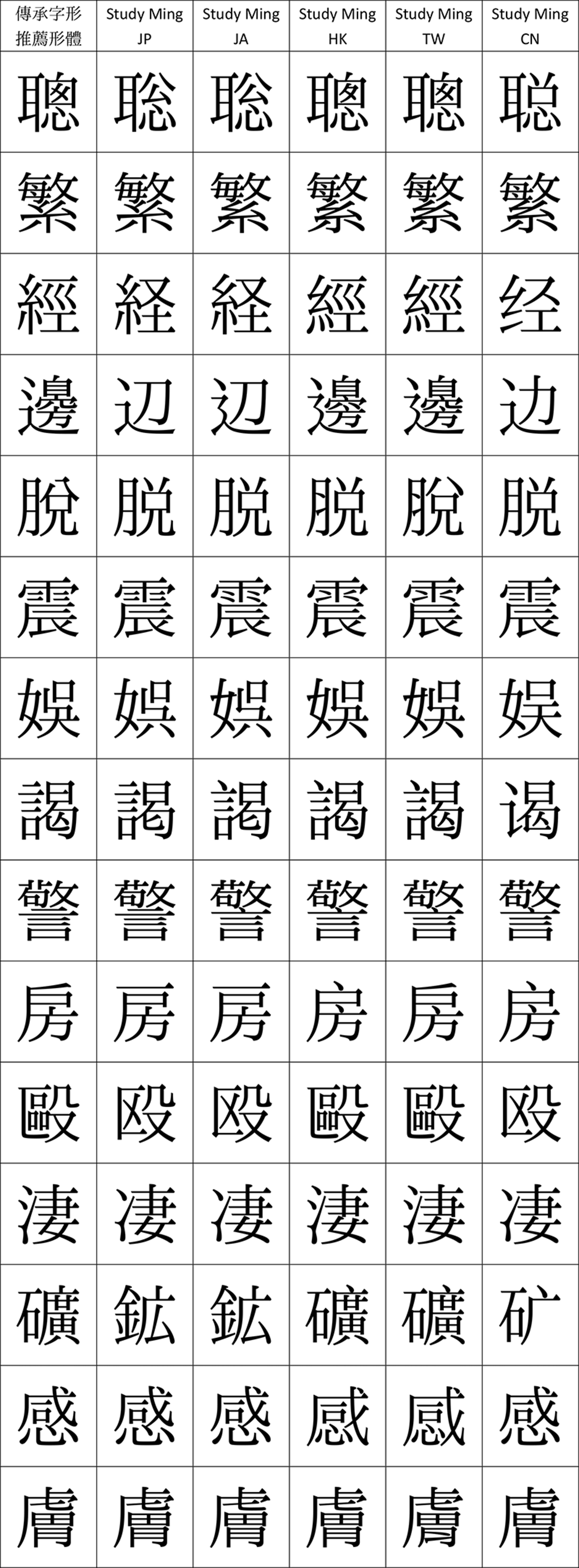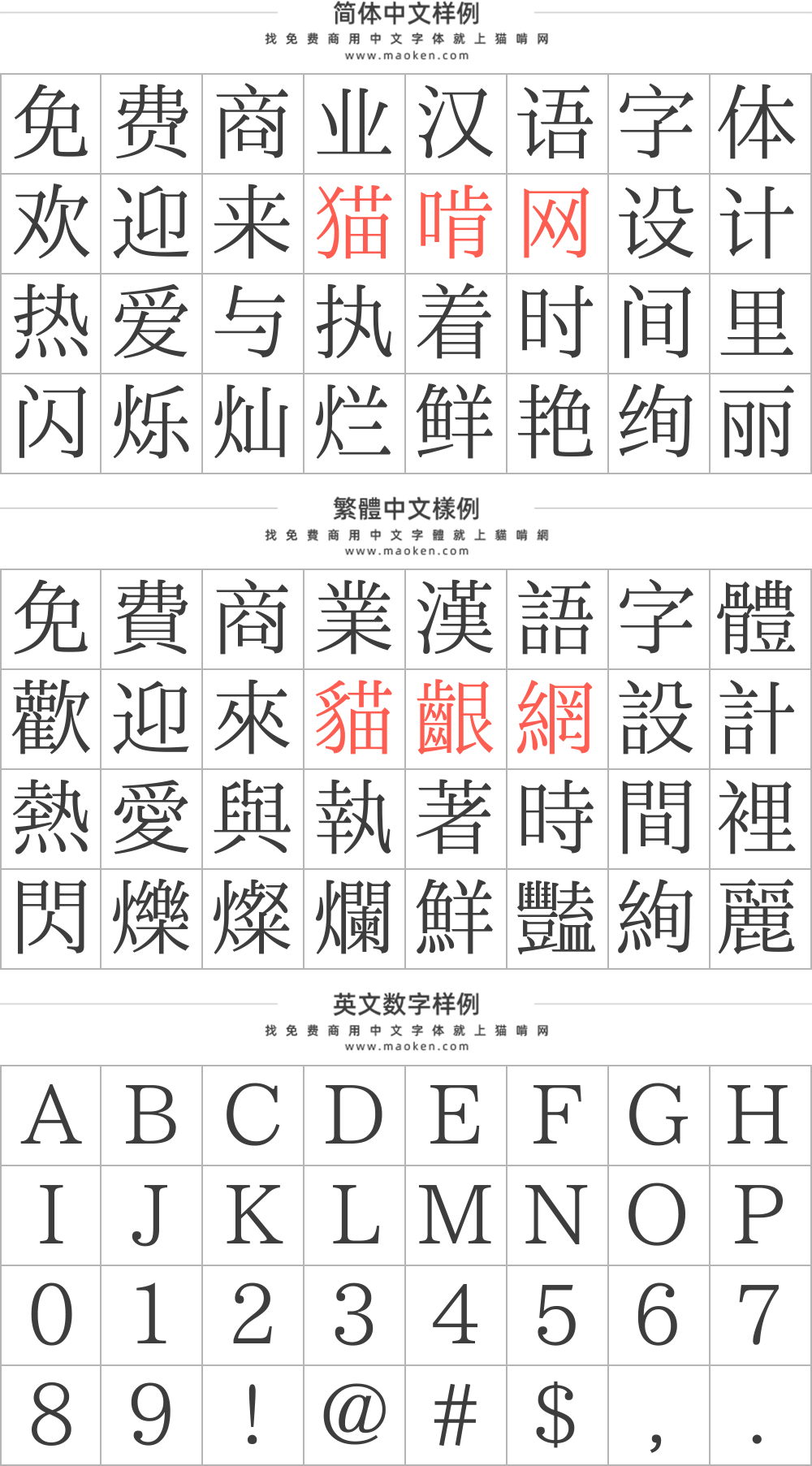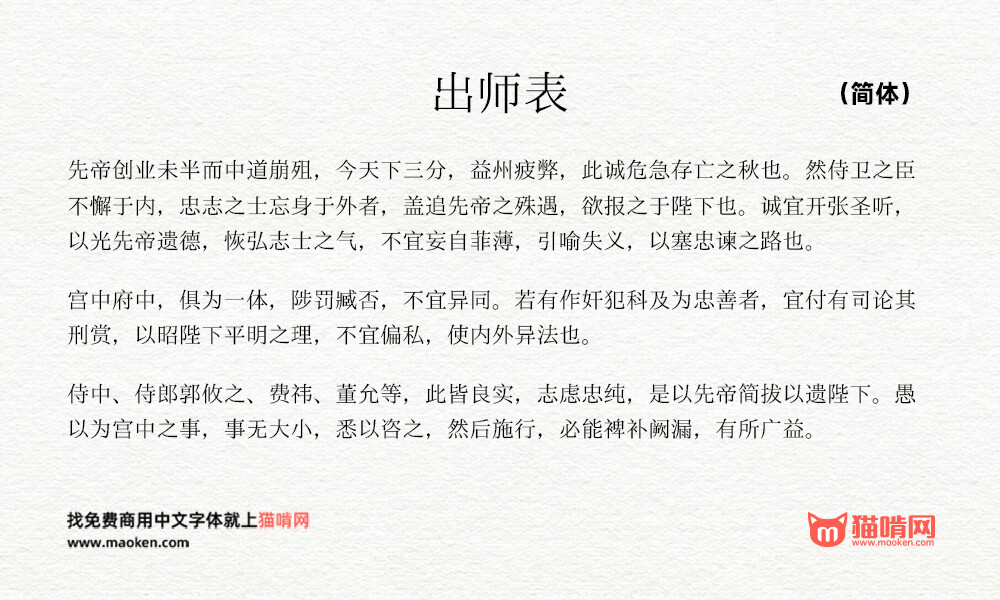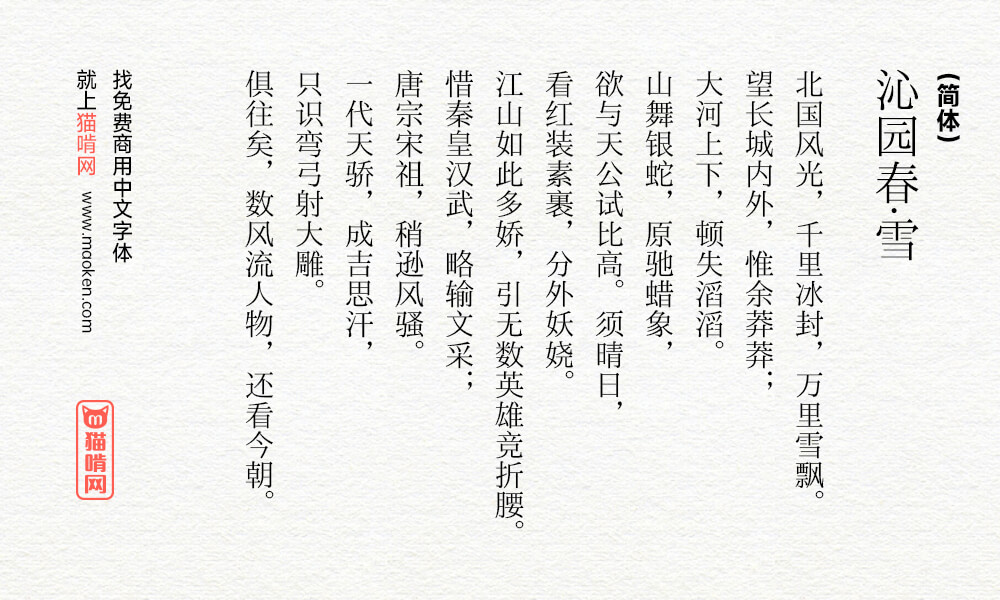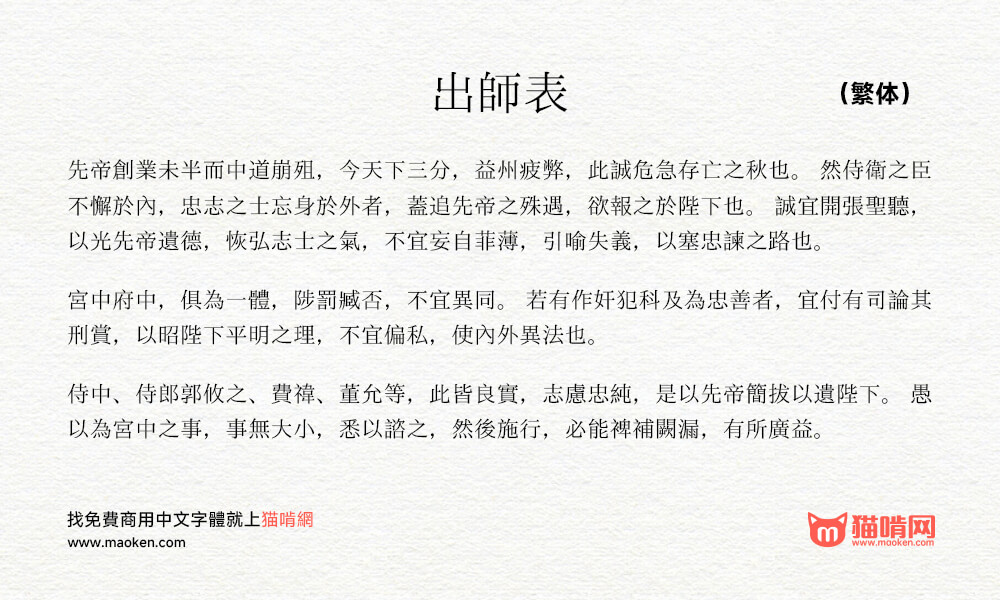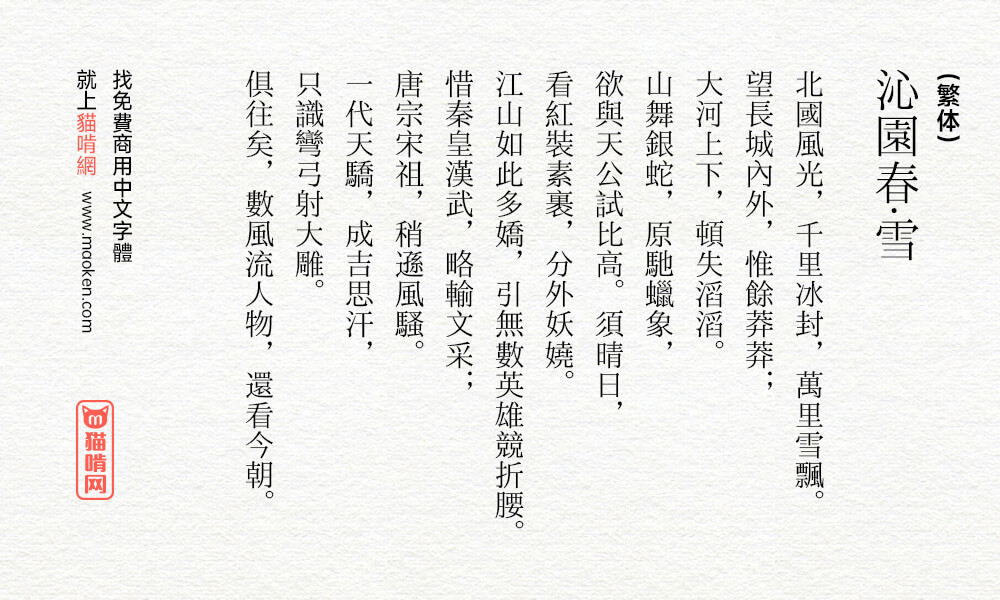
因汉字字形之硏究所需,目前没有符合硏究需求的字型可用,故启动本计划,制作符合需求之字型。目前的字型成品有:
Study Ming JP(学参明朝体 日本 印刷):
主要依《常用汉字表》(东京:文化庁,2010年),以及《常用汉字表の字体・字形に関する指针(报告)》(东京:文化庁,2016年)中的明朝体字形,检校、修改当中常用字的汉字字形。
Study Ming JA(学参明朝体 日本 教科书):
主要依《常用汉字表の字体・字形に関する指针(报告)》(东京:文化庁,2016年)中的教科书体字形﹐并参考表中的手书文字例子字形,以及モトヤ、モリサワ、イワタ等字型厂商的学参明朝体,检校、修改当中常用字的汉字字形。
Study Ming HK(学参明体 香港):
主要依《常用字字形表》(香港:香港特别行政区政府敎育局课程发展处中国语文敎育组,2012年)及《香港小学学习字词表》(香港:香港特别行政区政府敎育局课程发展处中国语文敎育组,2007年),并参考《常用字字形表(二零零年修订本)》(香港:香港敎育学院,2000年)和《香港电脑汉字参考字形》(香港:香港特别行政区政府政府资讯科技总监办公室、公务员事务局法定语文事务部,2017年),检校、修改当中常用字的汉字字形。
Study Ming TW(学参明体 台湾):
主要依《国字标准字体宋体母稿〈敎育部字序〉》(台北:敎育部国语推行委员会,1998年),并参考《国字标准字体楷书母稿〈敎育部字序〉》(台北:敎育部国语推行委员会,1998年)、《常用国字标准字体表》(台北:敎育部,1982年),检校、修改当中常用字的汉字字形。
Study Ming CN(学参明体 中国):
主要依《通用规范汉字表》(北京:敎育部、国家语言文字工作委员会,2013年),检校、修改当中常用字的汉字字形。
为方便不同语系的作业系统使用,避免在其他语系的作业系统或软件中失效,这些字型的实际名字都只有英文名。所有字型的字高、行高皆与一点字坊的新一細明體统一,除了可以与之搭配使用,亦能与视窗作业系统预设的「细明体」搭配,不会出现行高改变之问题。
本主要目的是为满足汉字字形硏研究的要求。字型的,不可能顾及设计美感,也欠缺时间仔细修改撤销。而且有些地方的敎育字形之规定,可能会与字型计划设计上的美感要求有冲突。因此若需要一般排印或显着说明,我们不建议采用这些字型。繁体中文的排印或显示,建议使用一点字坊的一点明体系列;简体中文的排印或显示,建议使用落霞孤鹜的霞鹜新致宋;日文的排印或显示,建议使用IPAmj明朝。
版本选择及技术难题
本修改初开展时,我们曾考虑基于思源字型或其衍生字型来编辑、。但是,我们发现有些思源字型使用了上一层的字型图形状和技术,以我们使用的字型图编辑软件打开,会进很多操作困难。版本(主)如果笔画未合并、可自动计算粗细度的版本)根本几乎无法编辑。有些版本虽然打得开,但许多编辑作业也变得简洁方便,字型档的生成也精密流畅。即使几经辛苦把文件生成,在MS中Word、MS Execl等软件中应用时,也经常遇到奇怪的问题,储存作或列印作pdf文件也失败。我们最终不得不放弃,白白文物有了时间和精力,从头到IPA系列的字型,把我们的编辑工作重新接过来。
有编修改字型需求的人,不一定是高阶技术需求者或狂热者。我们硏研究汉字字型,专注于汉学方面,却发现原来的字型并不合需求,不得不修改。即使我们无法掌握高阶技术,我们不认为我们的需求会受到关注。谨此呼吁有关方面,能够降低技术,使相关技术能力共享和授权应用。